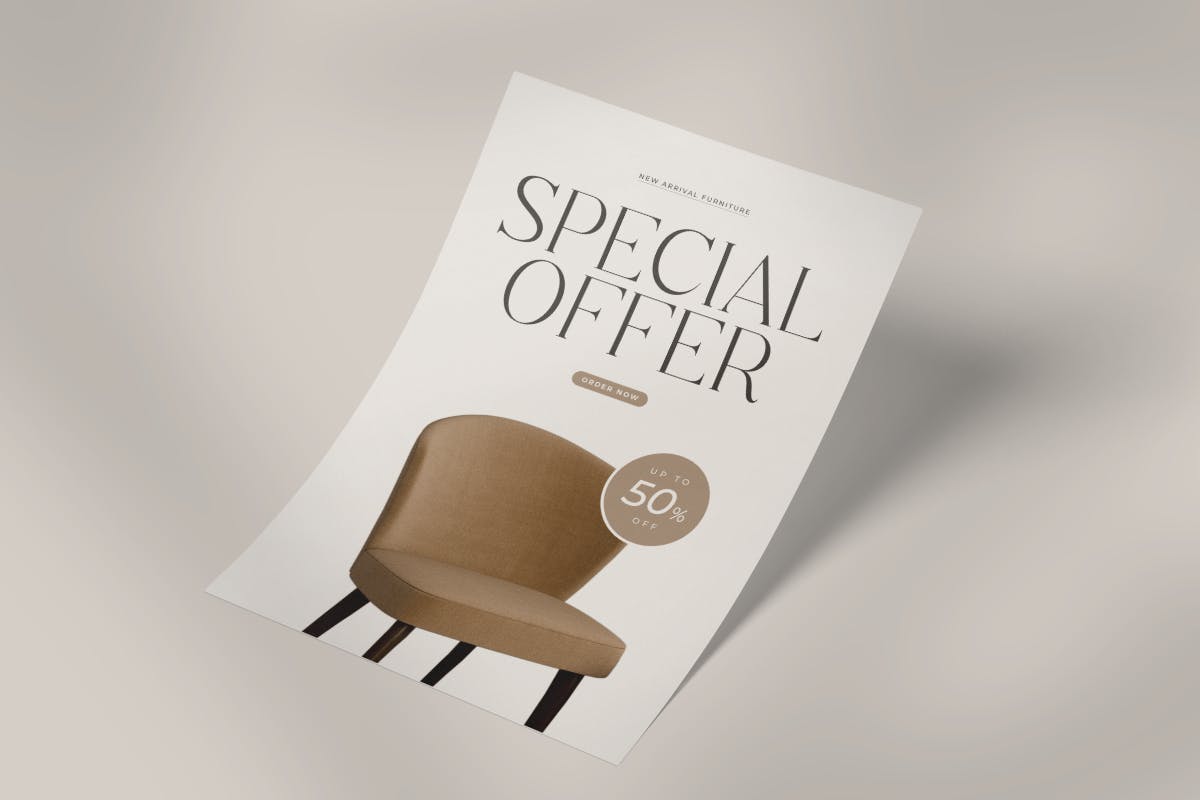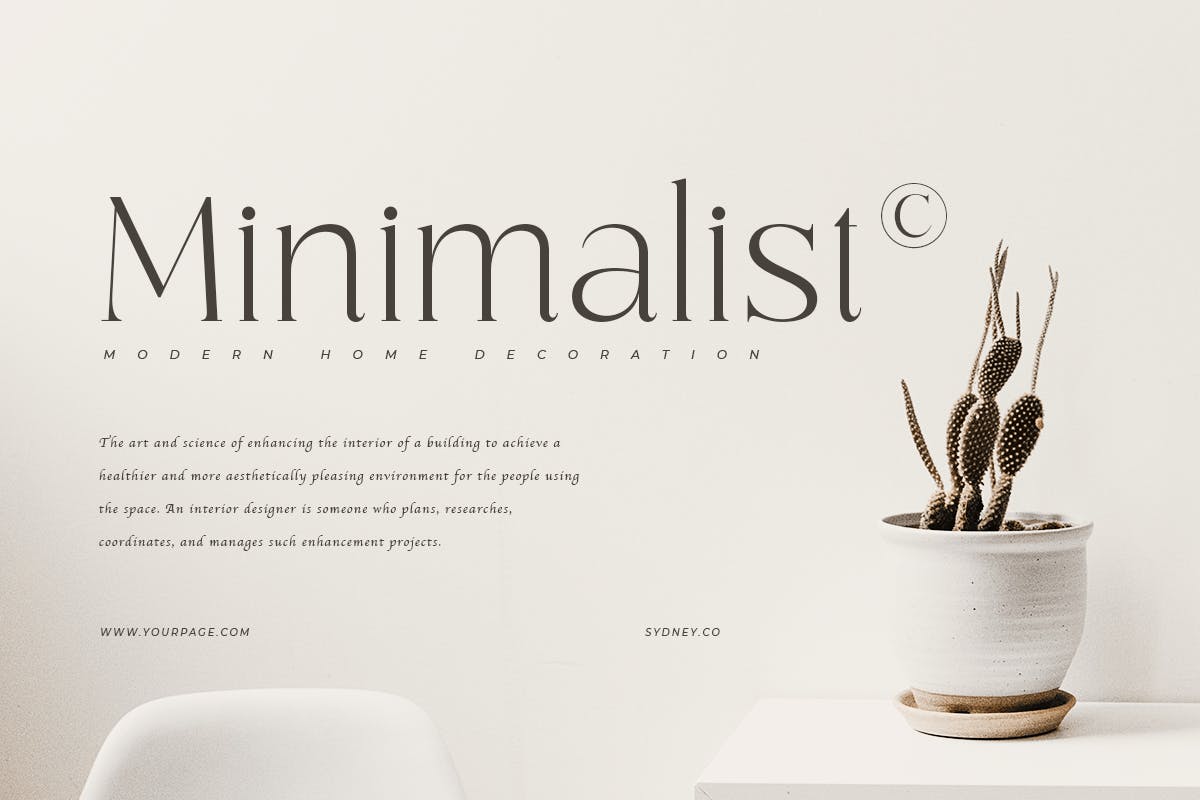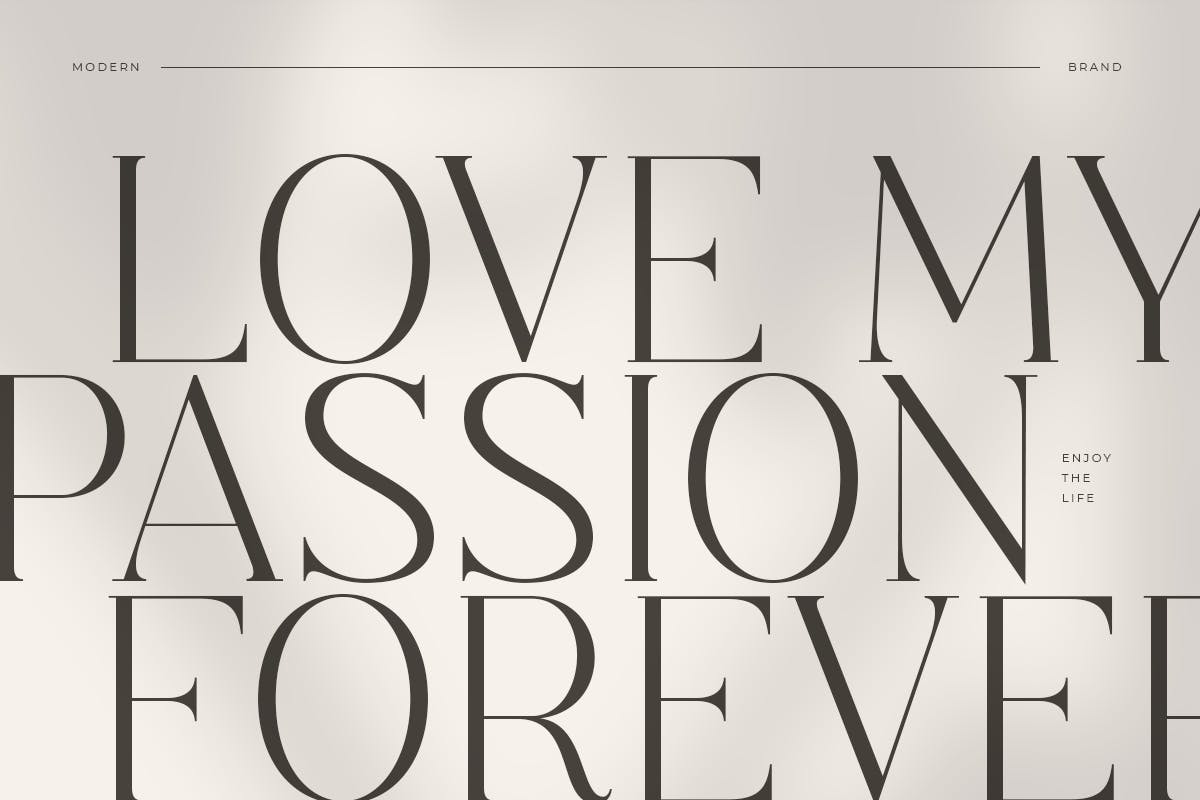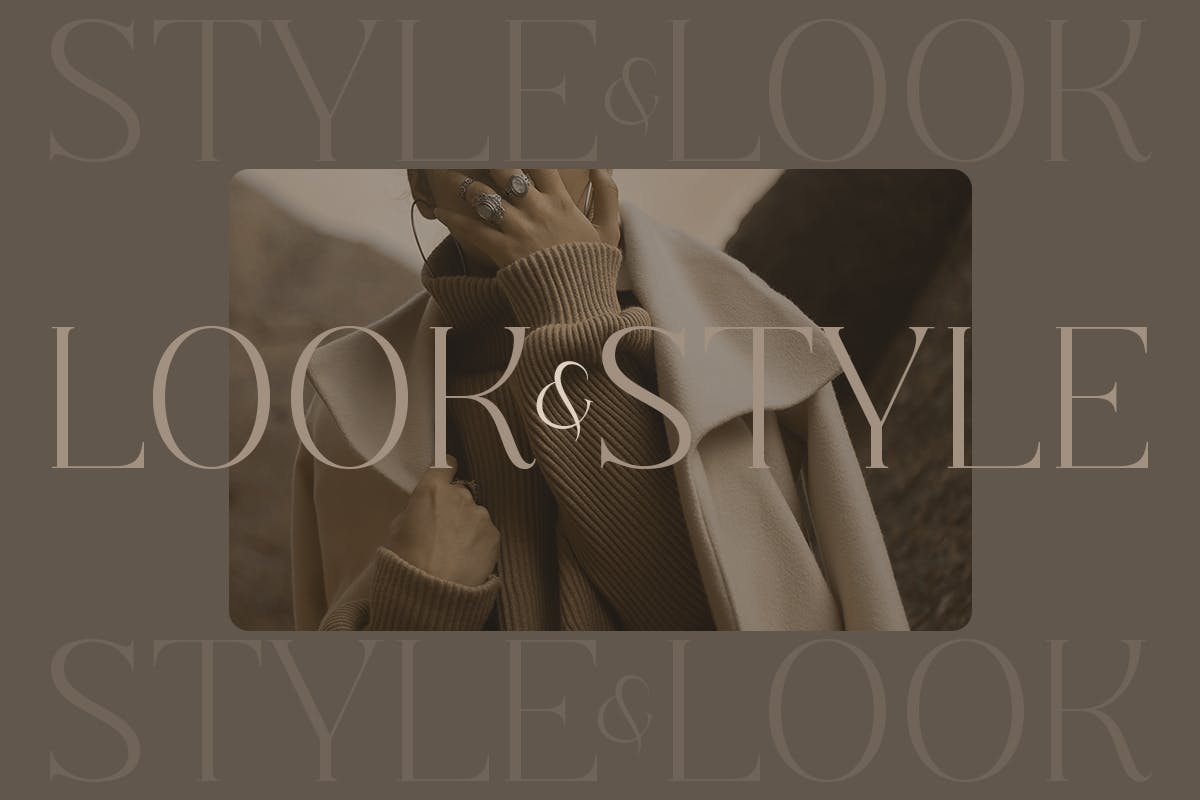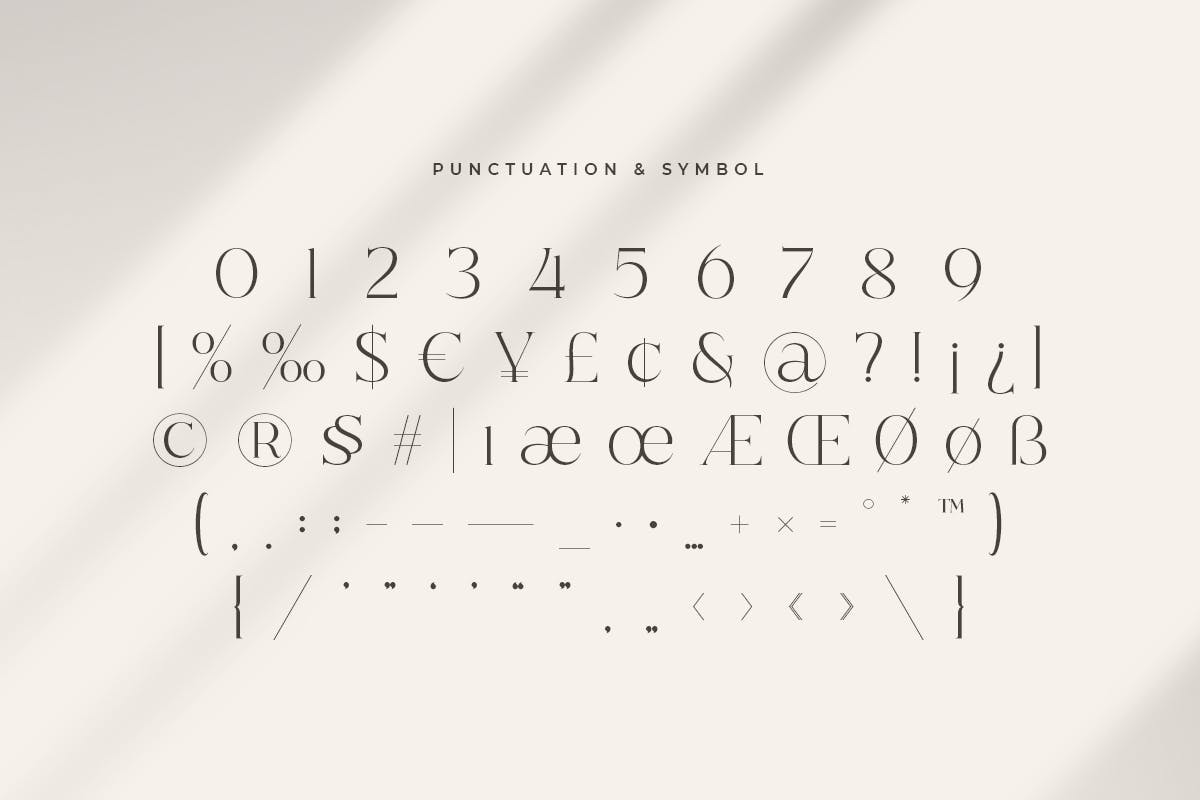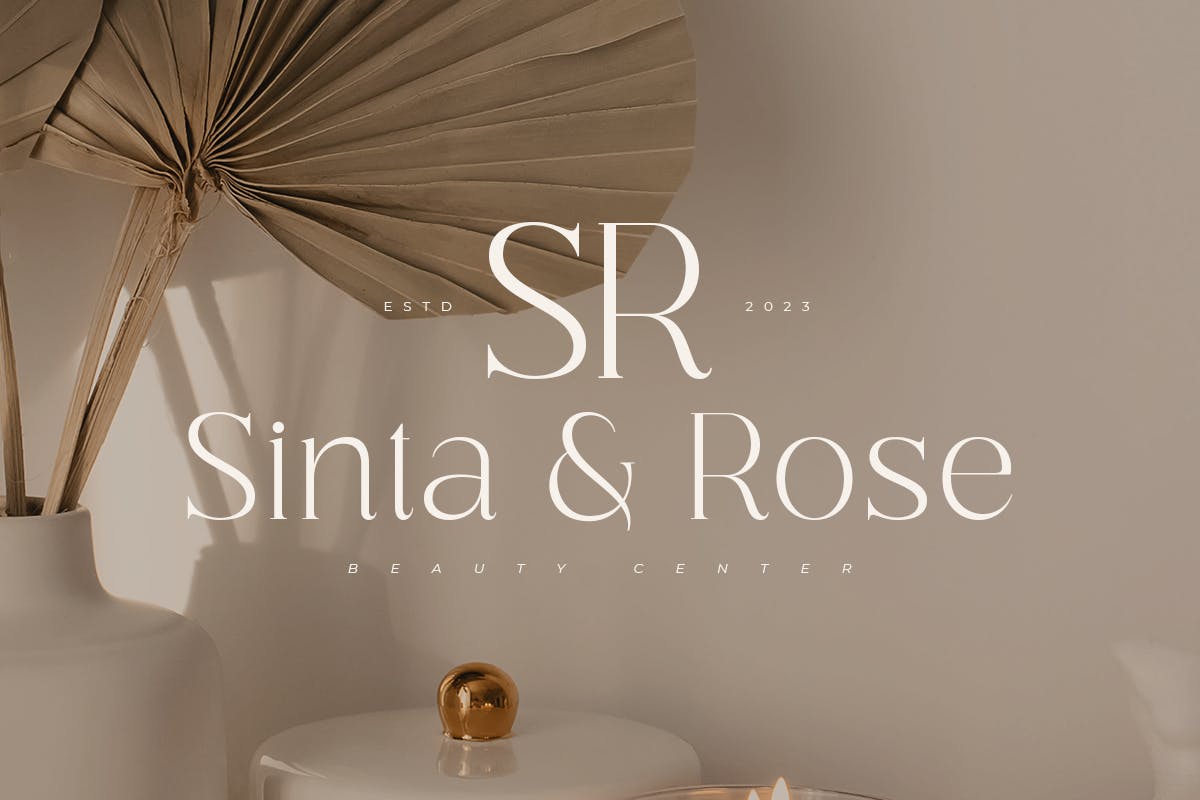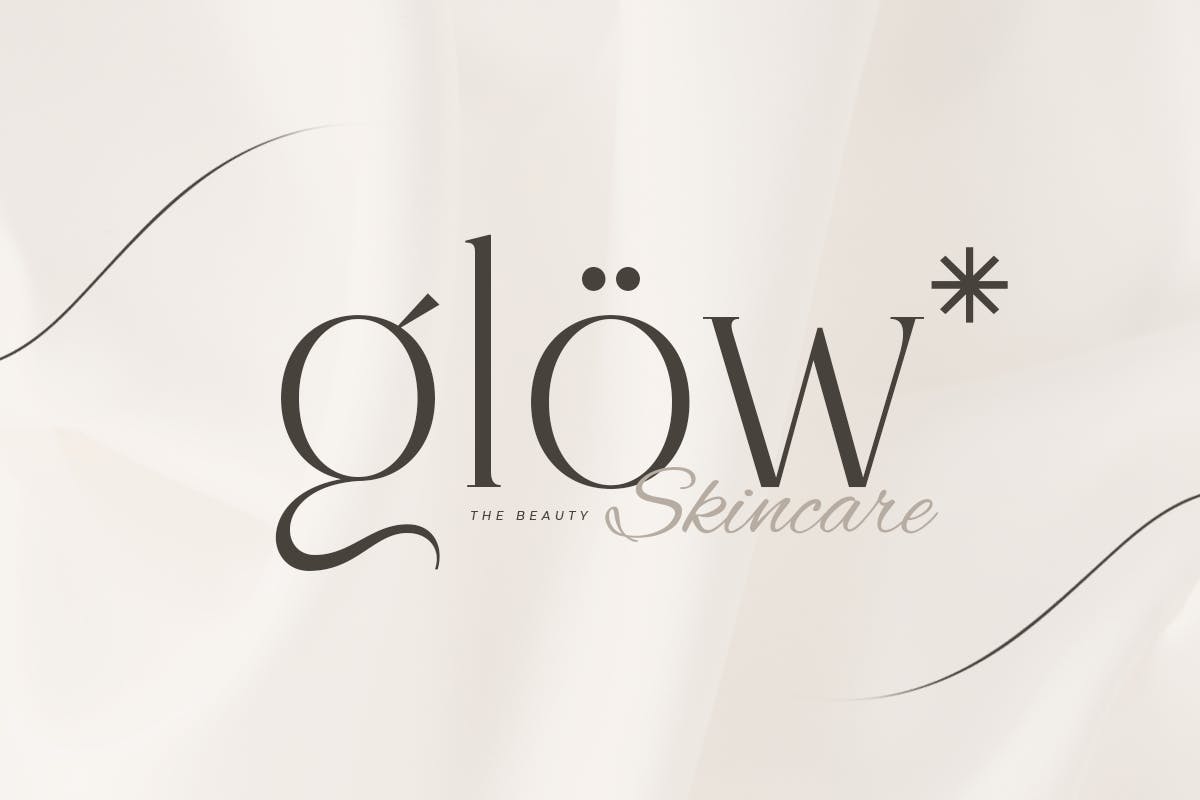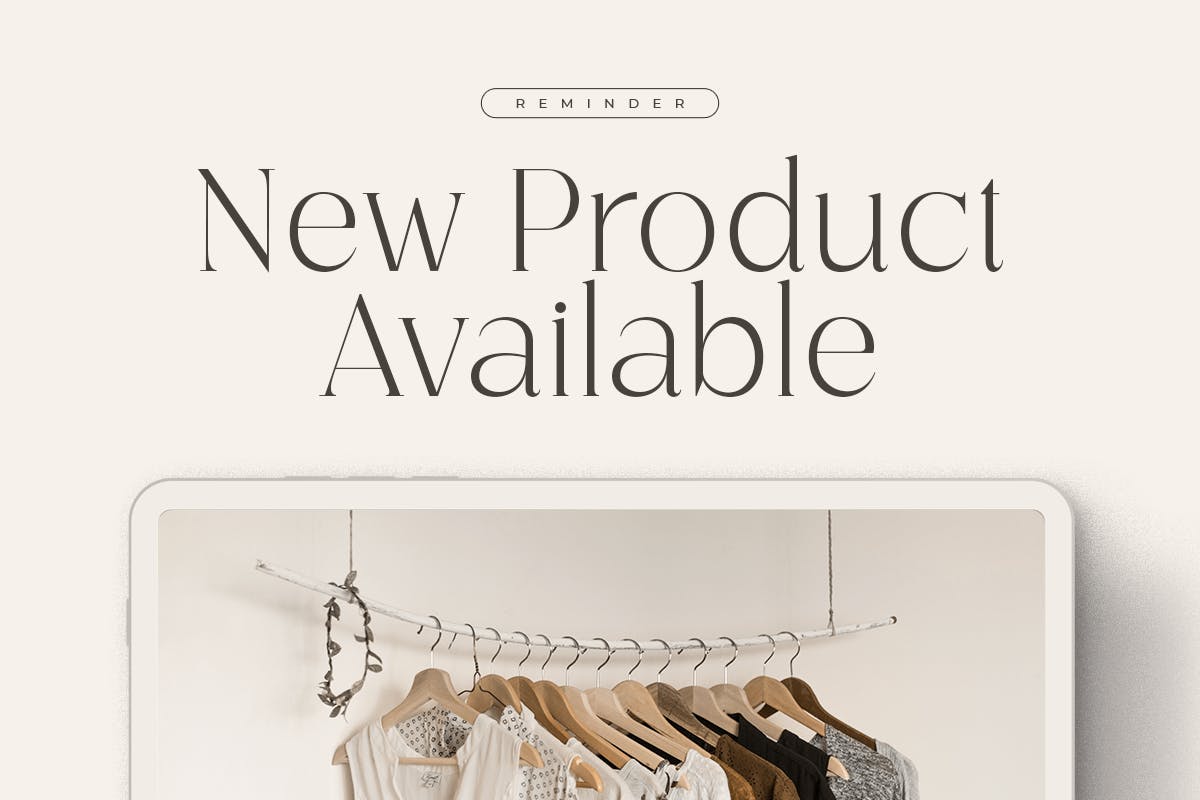
فونت Parisian یک فونت مدرن، زیبا و لوکس با طراحی سریف متعادل است که به راحتی میتوانید با انتخاب گزینههای مختلف، شکلهای منحصر به فرد و متنوعی ایجاد کنید. این فونت سریف نمایشگر با کنتراست متوسط، برای پروژههای برندینگ، لوگو، طراحیهای عروسی، پستهای شبکههای اجتماعی، تبلیغات، بستهبندی محصولات، طراحی محصولات، برچسبها، عکاسی، واترمارک، دعوتنامهها، لوازمالتحریر و هر پروژهای که نیاز به خوانایی بالا دارد، مناسب است.